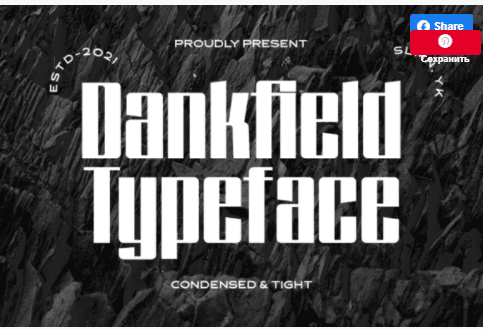
Dankfield Font
Dankfield - это жирный шрифт с толстыми буквами, который выглядит в стиле техно. Он будет отлично смотреться на множестве дизайнов, требующих футуристического, внушительного акцента.